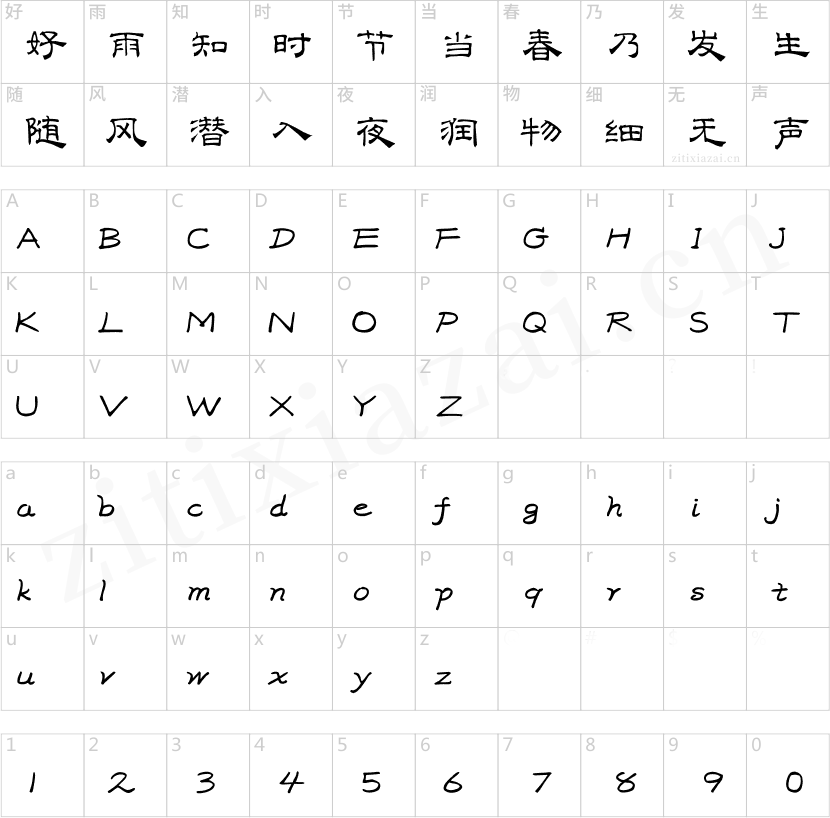
Aa未央宫词
Aa未央宫词字体
Aa未央宫词是一款非常具有艺术性的字体,它的设计灵感来源于对古典艺术的研究,同时又融入了现代字体设计的元素。字形优美,笔画粗细变化自然,给人以大气、典雅的感觉。Aa未央宫词是一款既传统又现代的字体,它的设计充满艺术感,美观大方,实用性也非常强。无论是对于设计师还是对于普通读者来说,都是一种非常不错的字体选择。Aa未央宫词适合用于具有艺术感的场合,比如海报、宣传单张、书籍封面等。由于其字形流畅且具有动态感,也适合用于大量的文本排版,如报纸、杂志等。